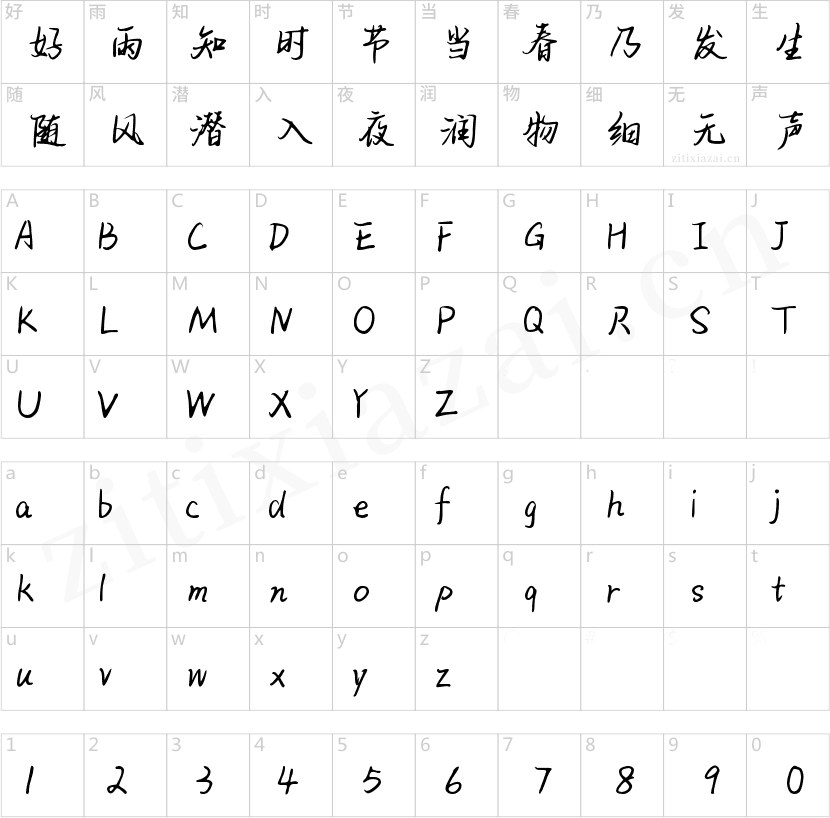
Aa我命由我不由天
Aa我命由我不由天字体
Aa我命由我不由天是一款非常具有艺术性的字体,它的设计灵感来源于对古典艺术的研究,同时又融入了现代字体设计的元素。字形优美,笔画粗细变化自然,给人以大气、典雅的感觉。Aa我命由我不由天是一款既传统又现代的字体,它的设计充满艺术感,美观大方,实用性也非常强。无论是对于设计师还是对于普通读者来说,都是一种非常不错的字体选择。Aa我命由我不由天适合用于具有艺术感的场合,比如海报、宣传单张、书籍封面等。由于其字形流畅且具有动态感,也适合用于大量的文本排版,如报纸、杂志等。